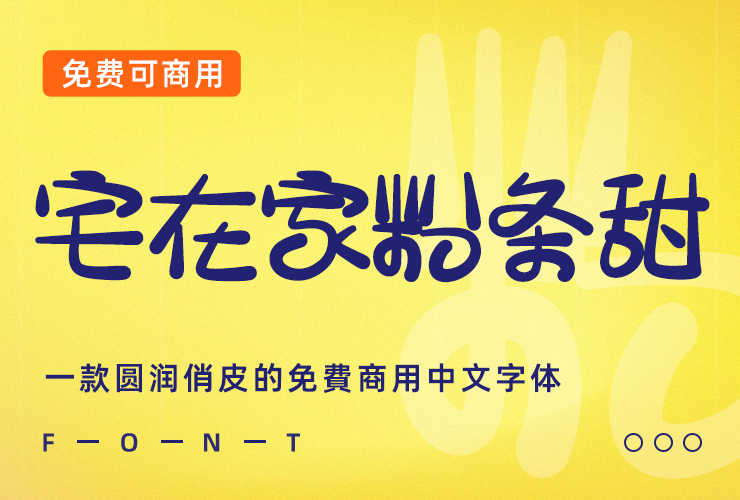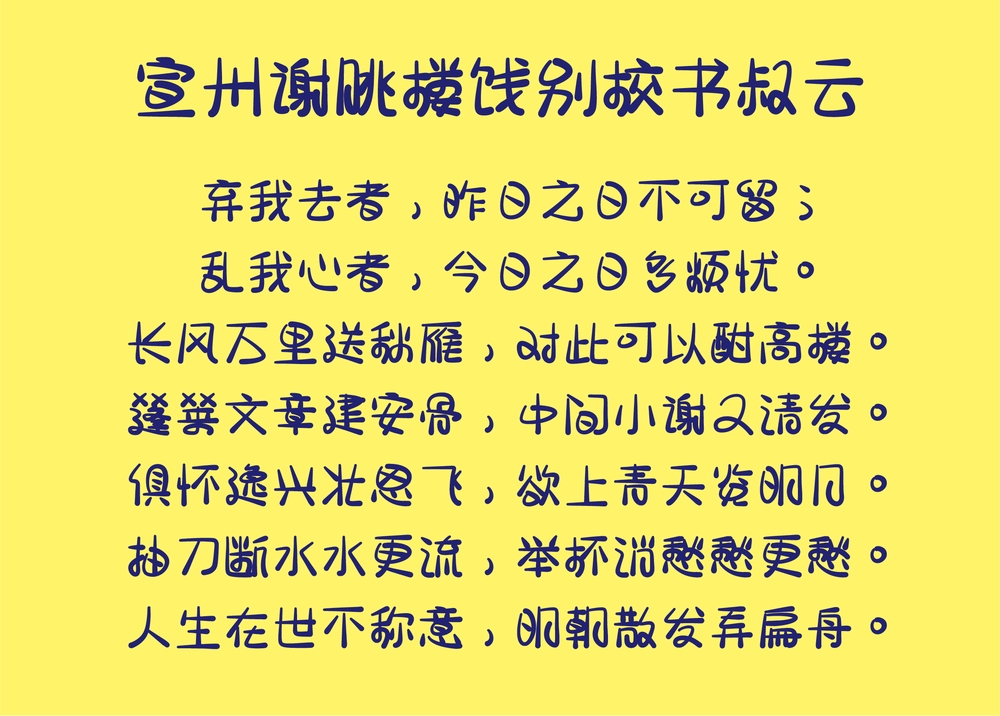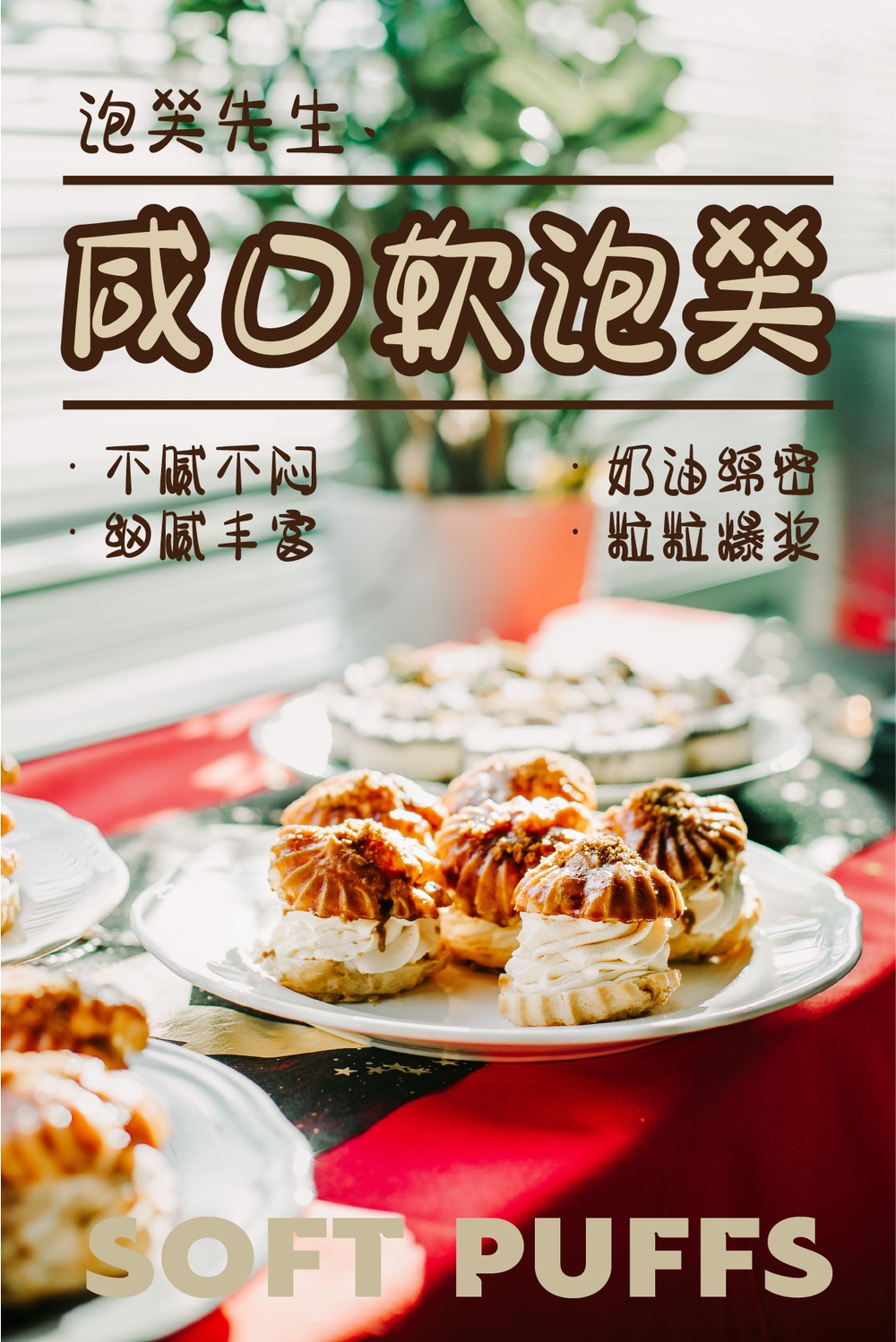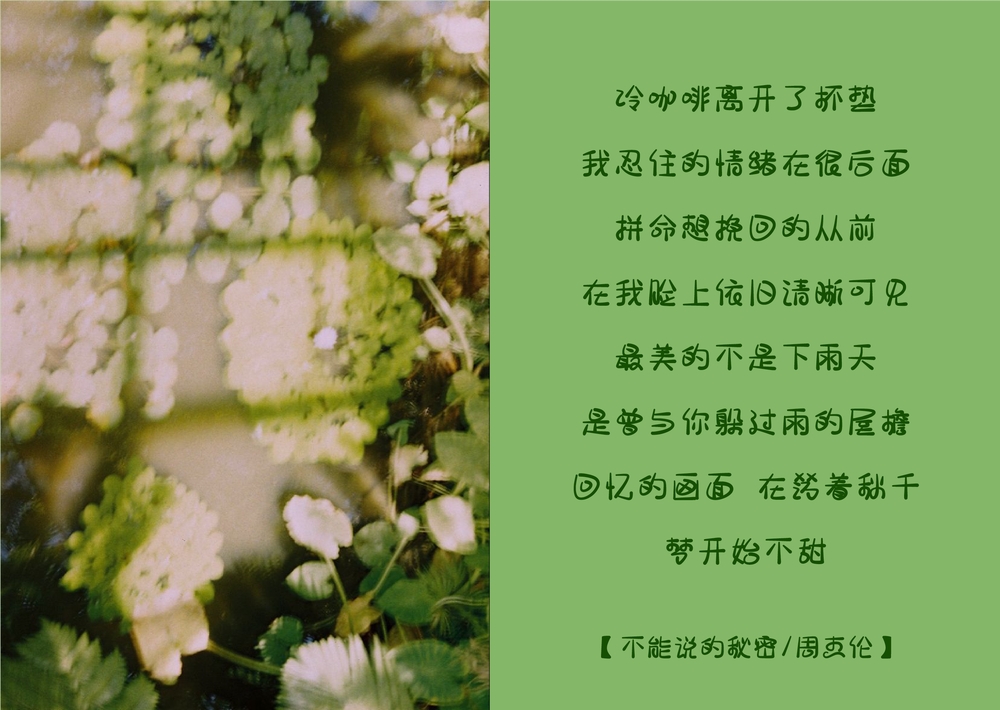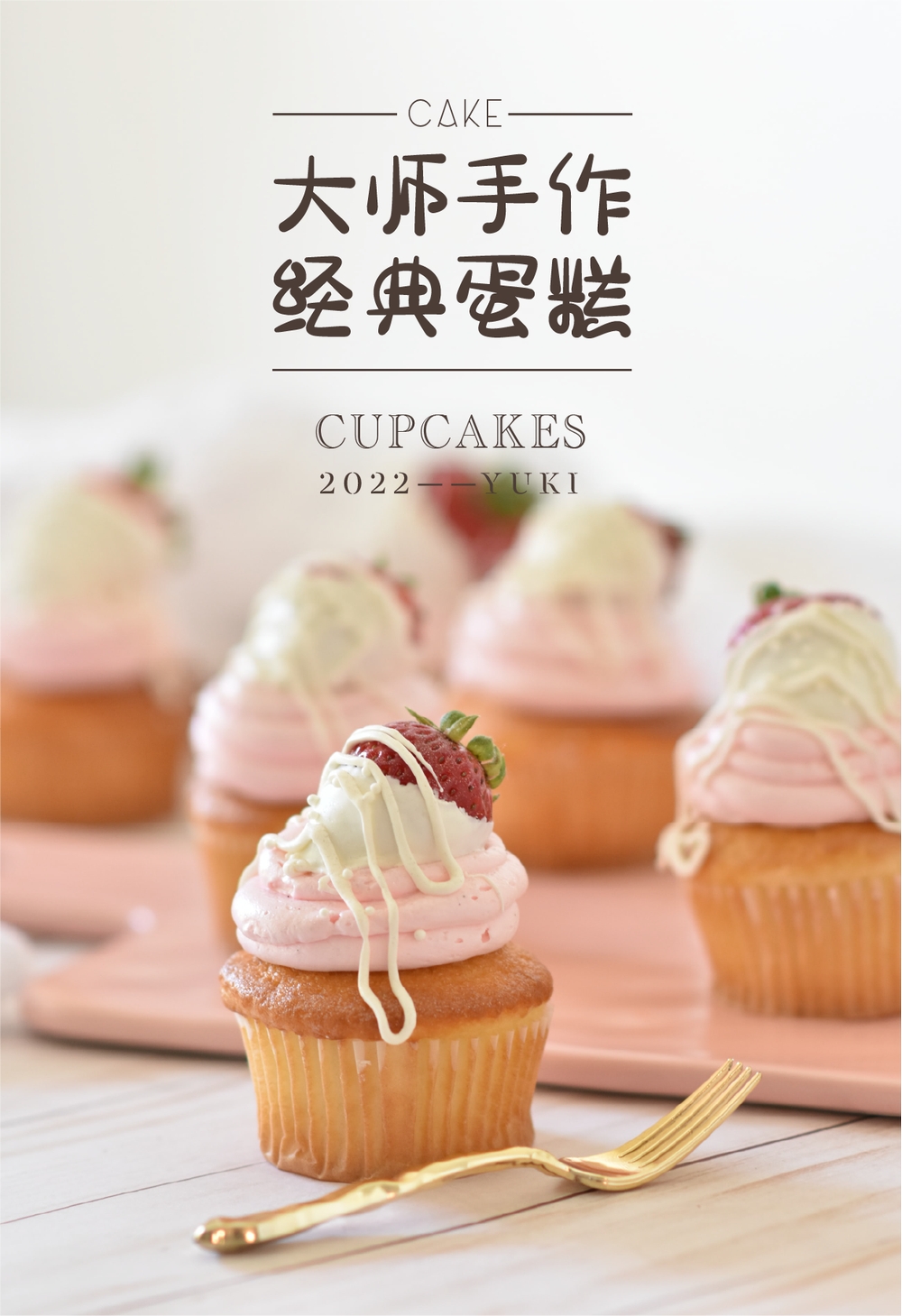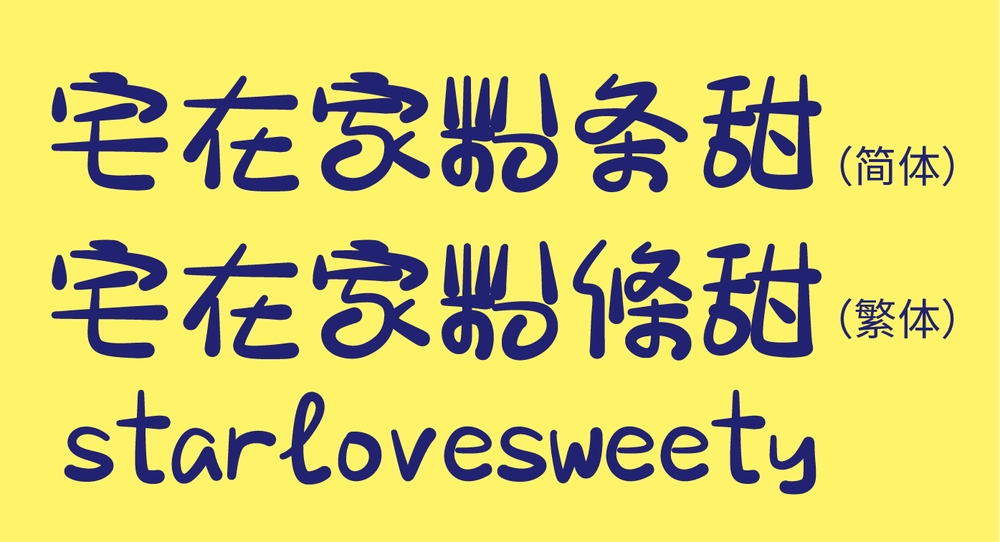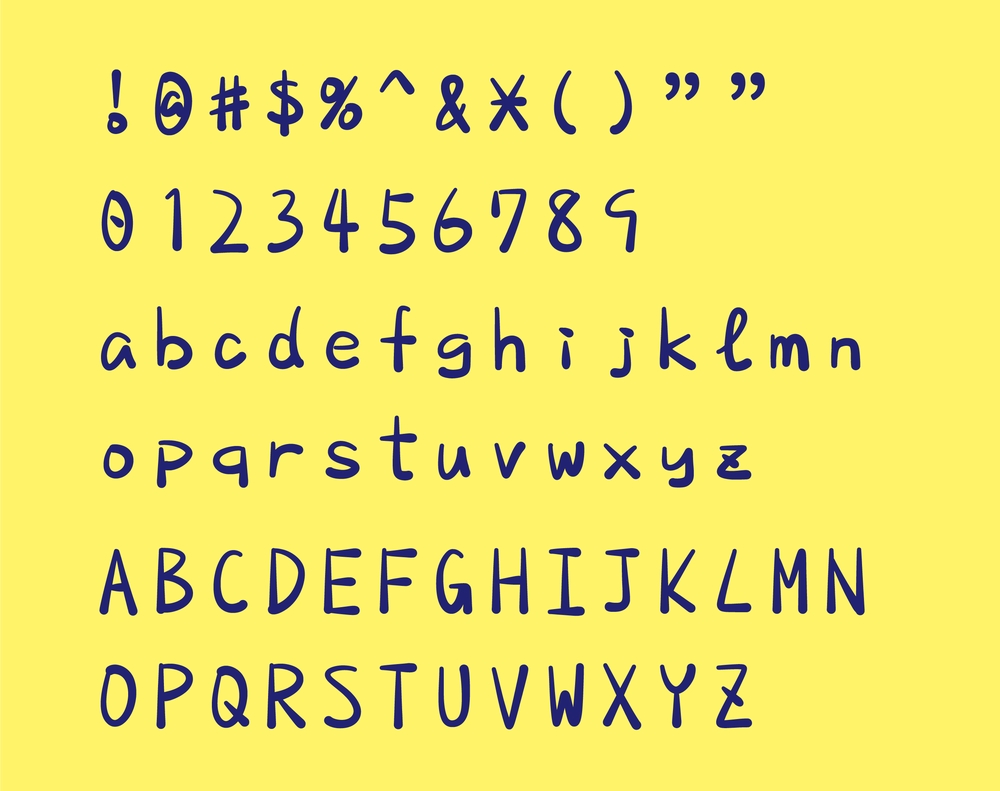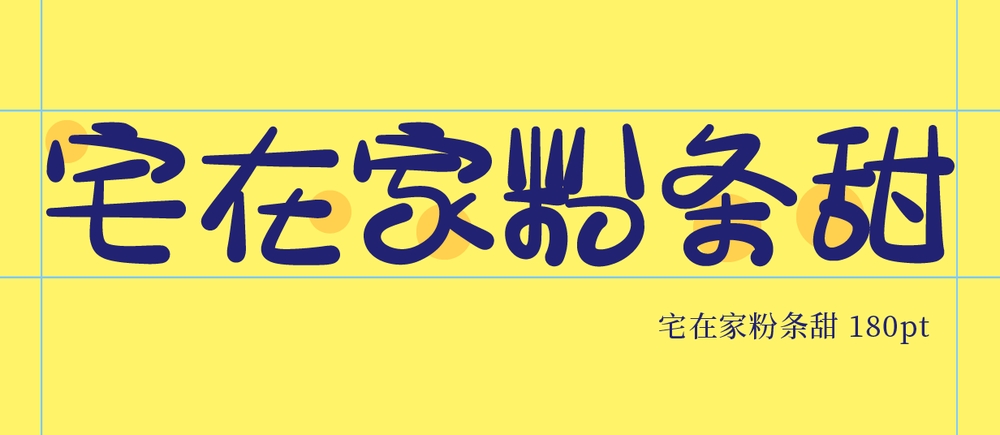
宅在家粉條甜(StarLoveSweety)是一个来自台湾省的网友“天天宅在家”创作而成的,在此字体发布前,设计师已经发布了 2 款宅在家系列字体,宅在家粉条甜是设计师推出的第三款免费字体。并且设计师为照顾到大陆简体字的习惯,完成了简体标准6763字,所以不用担心简体字的显示问题啦!这款字体对简体和繁体的都非常支持了~
「宅在家粉条甜」这是一款生动活泼,圆滑Q弹,小巧可爱的艺术字体。字体线条有粗有细,具有很好的视觉感,非常适合于文化宣传设计、商业类品牌广告、产品包装设计以及个性化文字排版等较多场景。